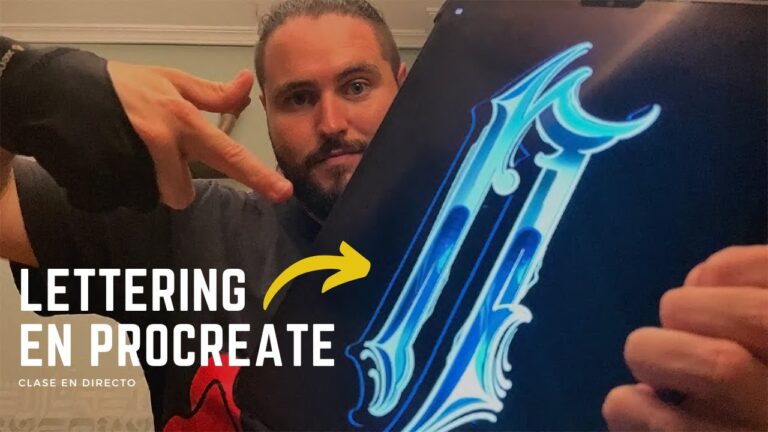
Técnicas Avanzadas de Tipografía en Procreate
En el mundo del diseño digital, las técnicas avanzadas de tipografía en Procreate se han convertido en herramientas esenciales para los creativos que buscan llevar sus proyectos al siguiente nivel. Esta poderosa aplicación no solo ofrece una amplia gama de herramientas para ilustración, sino que también permite experimentar con la tipografía de formas innovadoras y personalizadas. En este artículo, recorreremos cómo dominar estas técnicas puede transformar tu enfoque del diseño gráfico, dándote las habilidades necesarias para crear composiciones tipográficas impactantes y únicas.
¿Cómo se utilizan las fuentes en Procreate?
¿Cómo se puede escribir un texto en Procreate?
Para escribir un texto en Procreate, comienza eligiendo el pincel que más te guste, lo que te permitirá personalizar la apariencia de tus letras. Asegúrate de que el fondo esté transparente para que el texto destaque de manera práctica. Esta elección te dará la libertad de experimentar con diferentes estilos y tamaños, haciéndolo único y atractivo.
Una vez que hayas escrito el texto, selecciona la opción de lienzo y activa la ayuda de animación. Esto te permitirá añadir un nuevo fotograma en la línea de tiempo, facilitando la creación de animaciones dinámicas para tu texto. Así, podrás dar vida a tus ideas y hacer que tu diseño sea aún más cautivador y memorable.
¿Hay fuentes disponibles para Procreate?
Procreate ofrece una amplia variedad de fuentes que permiten a los artistas y diseñadores dar rienda suelta a su creatividad. La aplicación incluye una selección de tipografías predeterminadas que son versátiles y funcionales, perfectas para proyectos de ilustración y diseño gráfico. Además, los usuarios pueden importar fuentes personalizadas desde otras plataformas, lo que amplía aún más las posibilidades y opciones de personalización.
La opción de añadir fuentes personalizadas es especialmente valiosa para quienes buscan un estilo único en su trabajo. Existen numerosas plataformas en línea donde se pueden descargar fuentes gratuitas o de pago, lo que brinda la oportunidad de experimentar con diferentes tipografías que se adapten a la estética deseada. Esta flexibilidad permite a los creadores no solo destacar su trabajo, sino también mantener una coherencia visual en sus proyectos.
En resumen, la disponibilidad de fuentes en Procreate, tanto predeterminadas como personalizadas, facilita la creación de diseños atractivos y únicos. La capacidad de añadir tipografías específicas permite a los usuarios expresar su visión artística de manera más práctica, convirtiendo la aplicación en una herramienta esencial para cualquier diseñador o ilustrador que busque innovar y destacar en su campo.
Domina el Arte de la Tipografía Digital
La tipografía digital es una herramienta poderosa que puede transformar la percepción de cualquier proyecto visual. Con una amplia variedad de fuentes y estilos disponibles, elegir la tipografía adecuada no solo mejora la legibilidad, sino que también comunica la esencia de la marca. Es fundamental entender cómo la selección de tipografía puede influir en la emoción y el mensaje que se desea transmitir, creando una conexión práctica con el público objetivo.
Dominar el arte de la tipografía digital implica más que simplemente elegir una fuente atractiva; requiere un enfoque estratégico en la jerarquía, el espaciado y la alineación. Cada elemento tipográfico debe ser considerado cuidadosamente para asegurar que el diseño sea coherente y armonioso. Al perfeccionar estas habilidades, los diseñadores pueden elevar sus creaciones, logrando un impacto visual que no solo capte la atención, sino que también perdure en la memoria de quienes lo experimentan.
Crea Textos Impactantes en Procreate
Procreate se ha convertido en una herramienta esencial para los artistas digitales, y su capacidad para crear textos impactantes es inigualable. Con una interfaz intuitiva y una variedad de pinceles personalizables, puedes diseñar tipografías que no solo comunican un mensaje, sino que también capturan la atención de la audiencia. Desde letras fluidas hasta estilos más geométricos, Procreate te permite experimentar con diferentes formas y colores para dar vida a tus ideas.
El uso de capas en Procreate es fundamental para lograr un acabado profesional en tus textos. Al trabajar en capas, puedes ajustar cada elemento de tu diseño sin afectar el resto, lo que te brinda una gran flexibilidad. Además, la posibilidad de aplicar efectos como sombras, brillos y texturas en cada letra añade profundidad y carácter a tus creaciones, permitiéndote destacar en un mundo visual saturado.